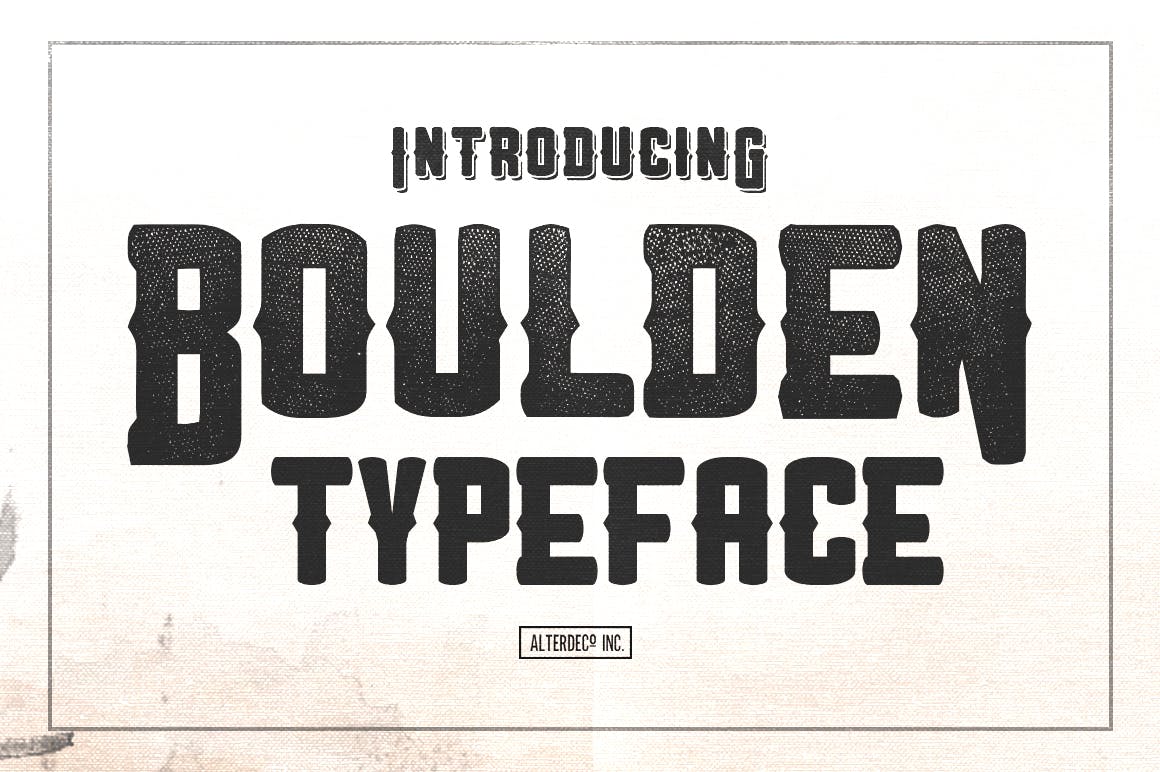
Boulden Typeface
Police de caractères Boulden
Boulden est audacieux ! toutes en majuscules! parfait pour votre affiche de propagande, ou même un graphisme moderne et vintage. il est disponible en 3 styles différents avec lesquels vous pouvez jouer, style régulier, grunge et ombré.